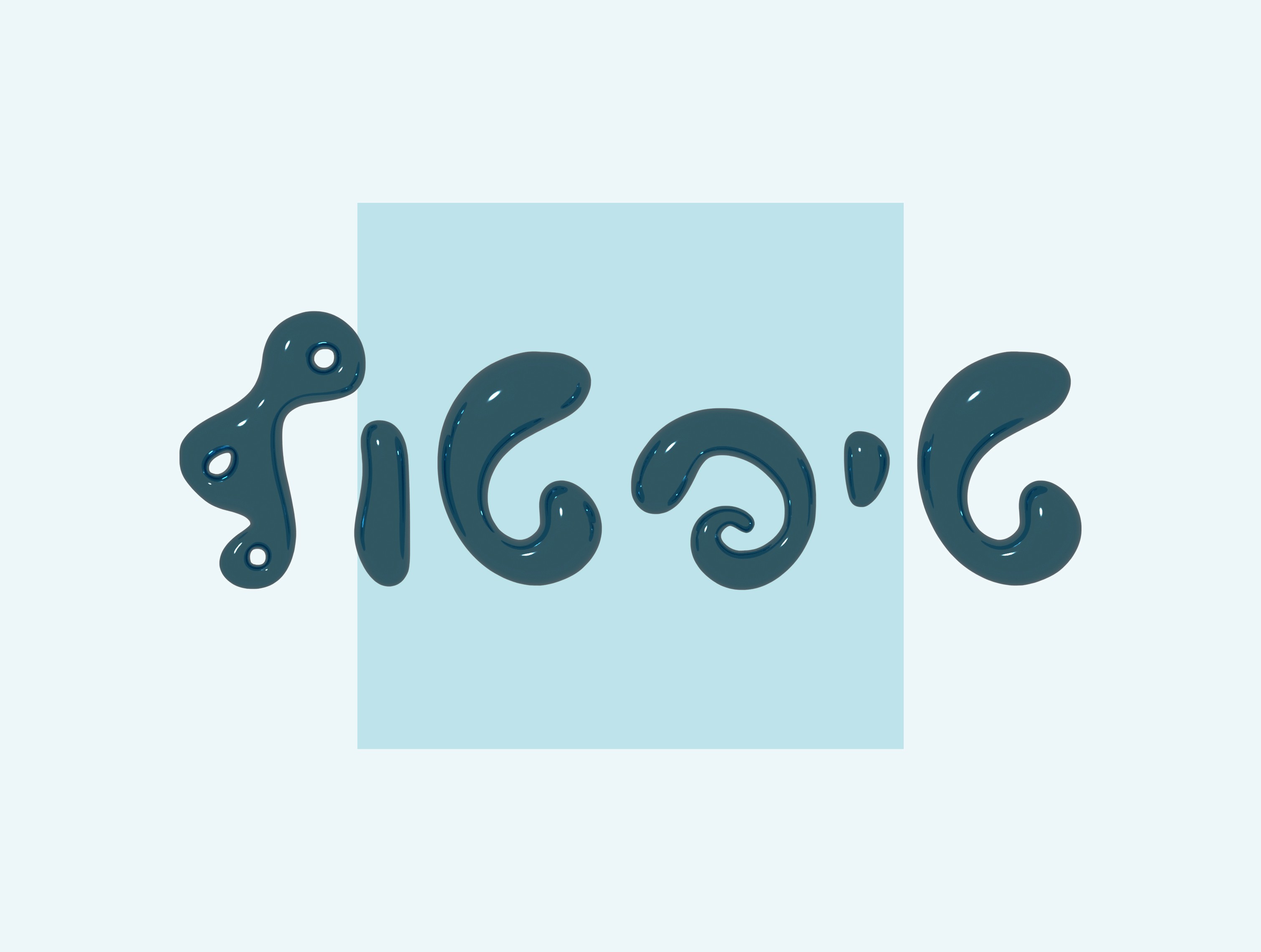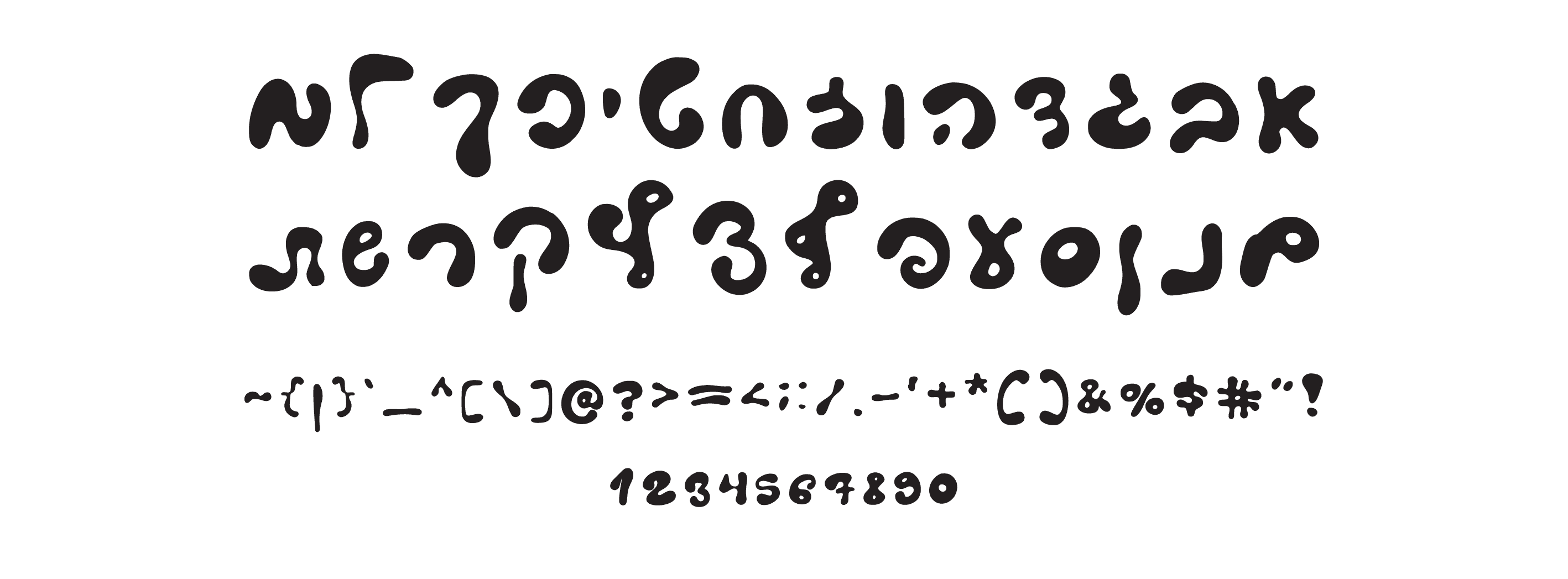
פונט טיפטוף
פונט עברי נוזלי, יצירתי וייחודי, שמזכיר טיפות צבע וקומיקס.
טיפטוף — הפונט שזורם על המסך
דמייני טיפת מים שמטיילת לה, זזה, משנה צורה, ומזמינה אותך לחייך.
טיפטוף הוא פונט עברי חופשי, נוזלי וייחודי, שמרגיש כמו שילוב בין קומיקס, אמנות רחוב וג'לי צבעוני.
האותיות בו זורמות, מתעגלות ונראות כמו טיפות צבע שמתחברות למילים — פונט שלא לוקח את עצמו ברצינות, אבל משאיר רושם עיצובי בלתי נשכח.
הוא מתאים לעיצובים שמבקשים לפרוץ את הגבולות ולהכניס נגיעות של הומור, כיף וקריצה גרפית מפתיעה.
איפה הוא מרגיש בבית?
🍭 לוגואים של ממתקים או משחקים
🎨 פוסטרים לפסטיבלים או אירועים אמנותיים
🌈 עיצובים גרפיים יצירתיים ומופרעים
🎥 כותרות לפרויקטים אנימטיביים, קליפים וסרטונים צבעוניים
למי הוא מתאים?
למעצבים חובבי ניסויים גרפיים, למותגים שמכוונים לילדים או צעירים, ולכל מי שמחפש פונט שמקפיץ כל עיצוב לחיים.